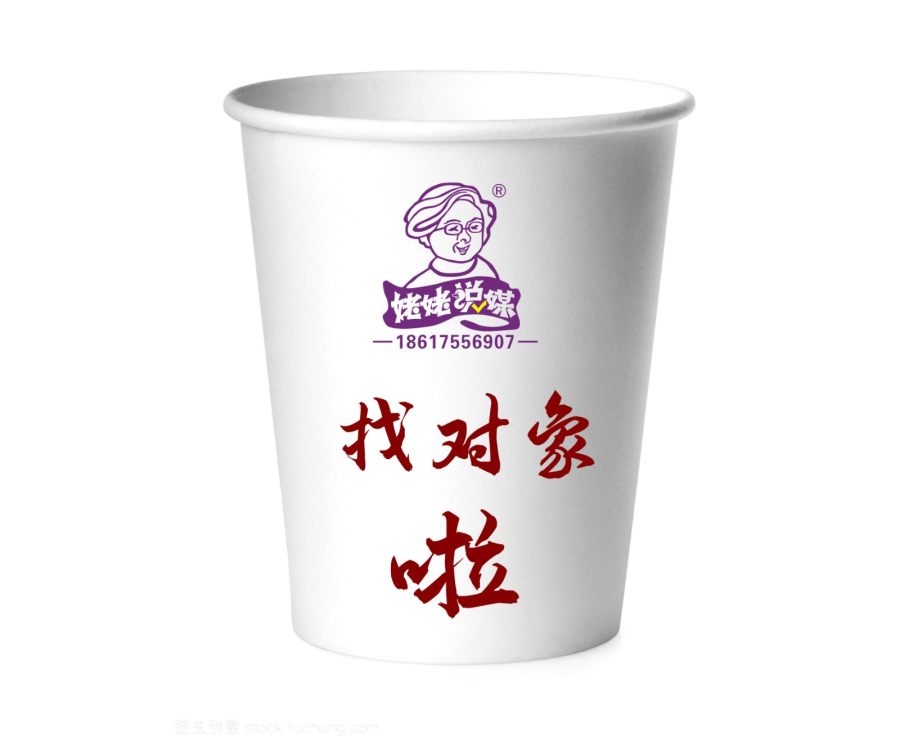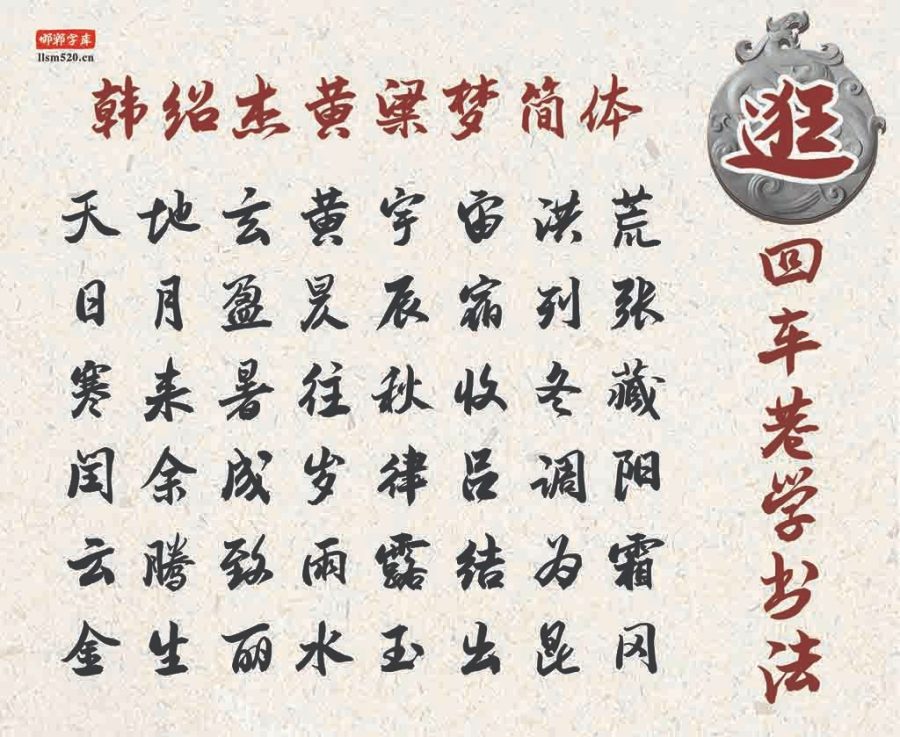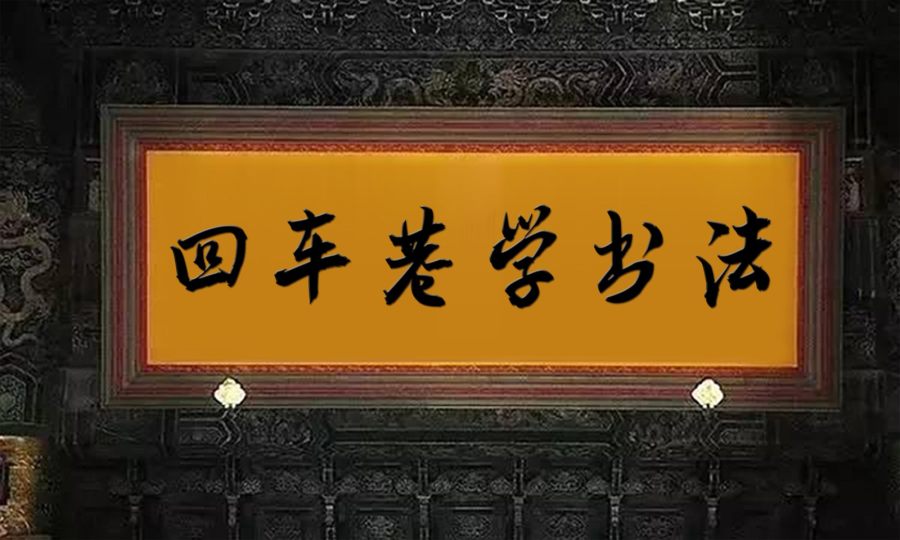
适用于书籍的封面书法大字下载
字体视界新上线了一款韩绍杰黄粱梦简体,该字体用笔灵动多变,爽利中见力量,飞白劲健而又沉着,起收笔、提按、 顿挫随心所欲,姿态飞动,中侧锋并用,变化莫测,"风樯阵马 ,沉着痛快”,自称"八面出锋”,体势多欹侧,章法疏密相间。属于书法大字榜书范畴,适用于书籍的封面,以及品牌广告和产品包装设计尤其适合做古籍牌匾用字。